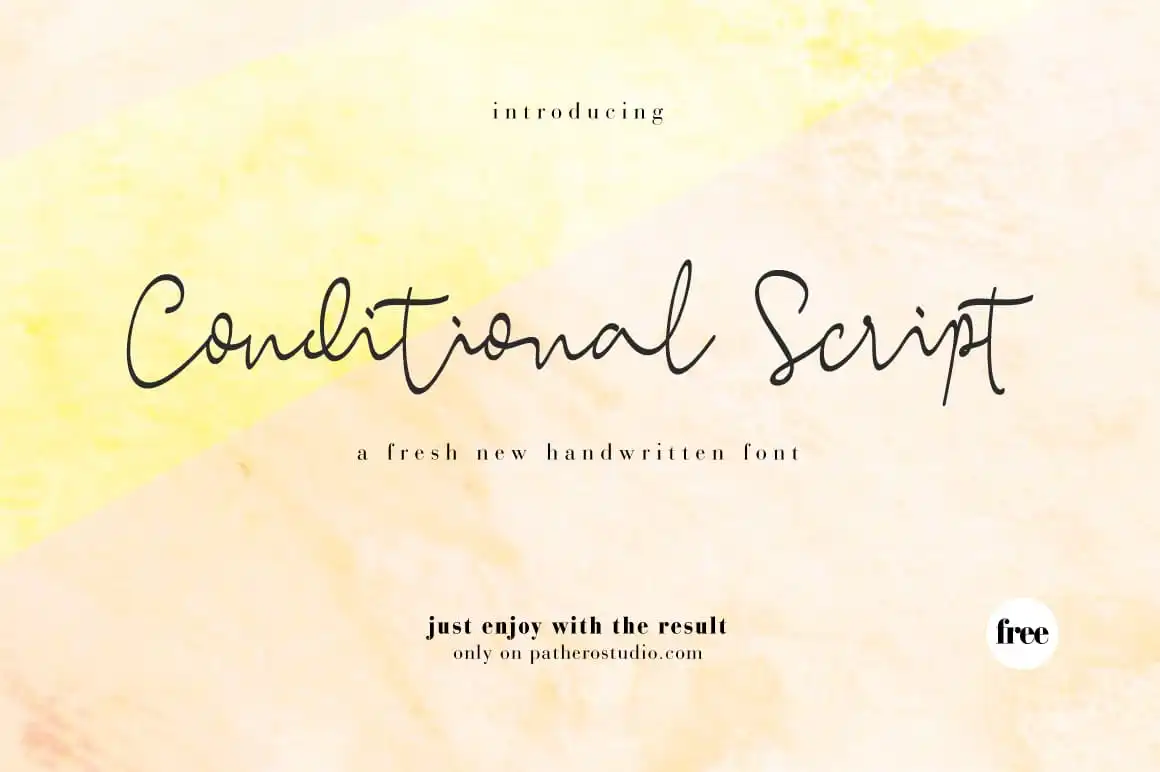
Conditional Script Font – Download Grátis
A fonte Conditional é uma criação única e autêntica, inspirada na escrita à mão de Hamilton. Essa elegante tipografia script, perfeitamente concebida para atender às necessidades modernas do design gráfico, possui um encantador fluxo que permite você usar-a em textos grandes para dar-lhes uma pitada de personalidade. Ideal tanto para conteúdo de branding quanto para embalagens ou materiais de mídia social, a Conditional oferece um toque inusitado que adiciona profundamente valor ao seu design. Suas linhas e curvas fluidas garantem que você consiga transmitir sua mensagem de uma maneira única e atraente. Sua utilização em textos ampliados permite que o design adquira um ar jovial e único, criando um padrão distintivo para qualquer projeto que esteja trabalhando. Independentemente do canal pelo qual seu conteúdo será apresentado – seja redes sociais, embalagens de produtos ou materiais impressos – a Conditional é certamente uma fonte perfeita que adiciona aquela pitada especial e inovadora ao seu design visual.